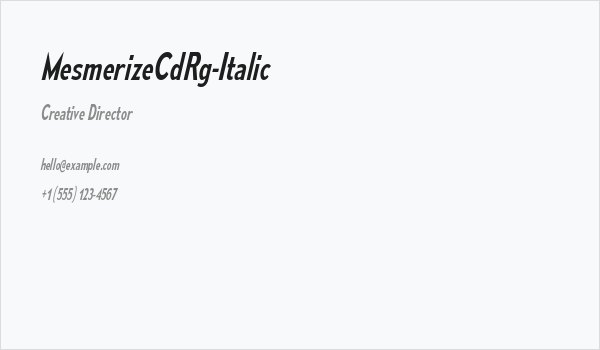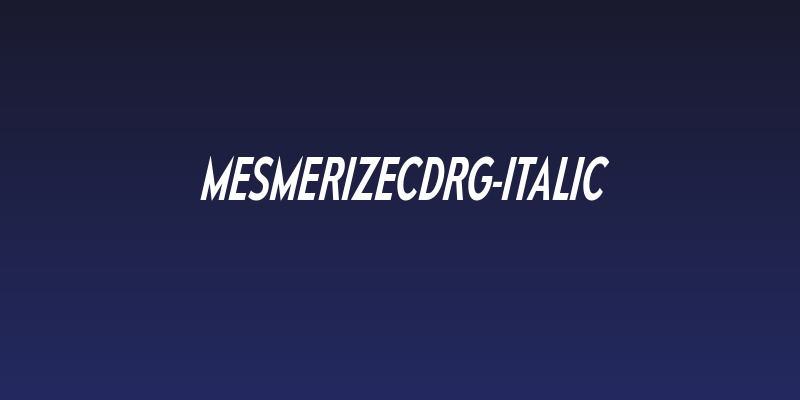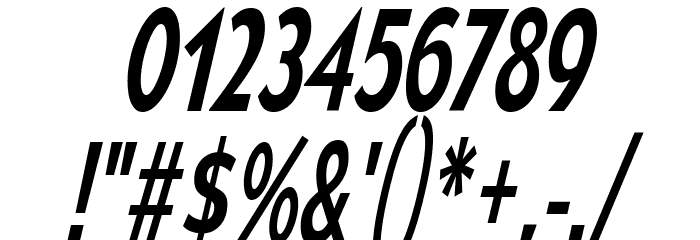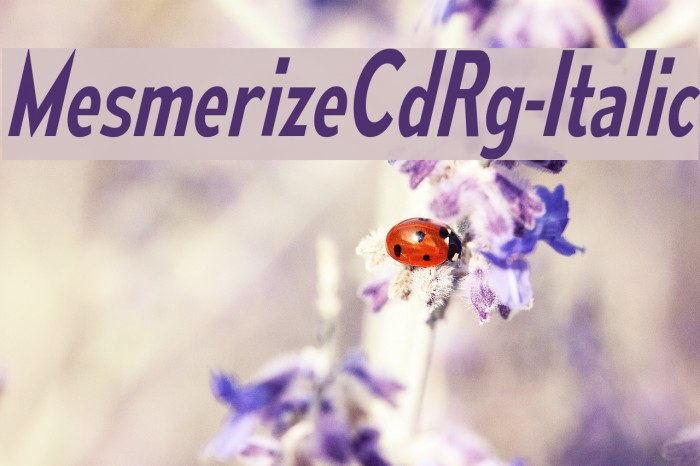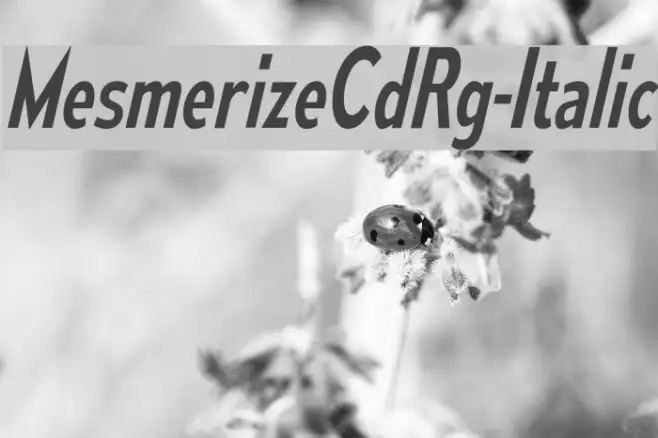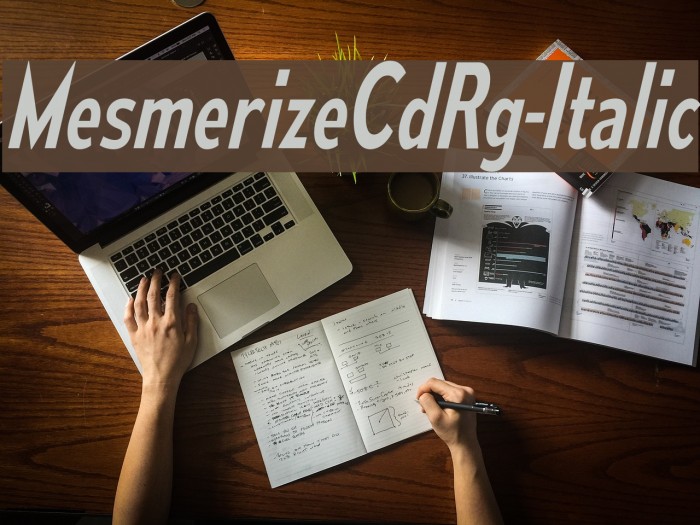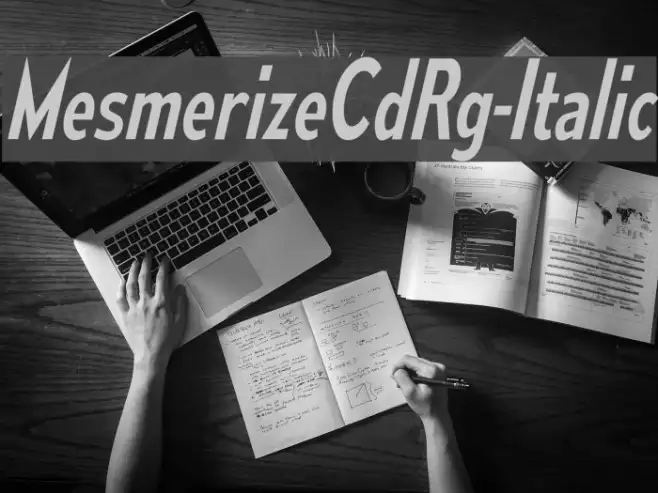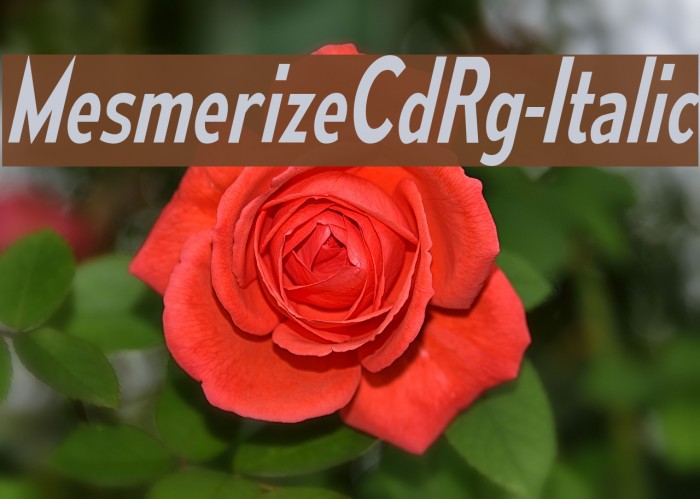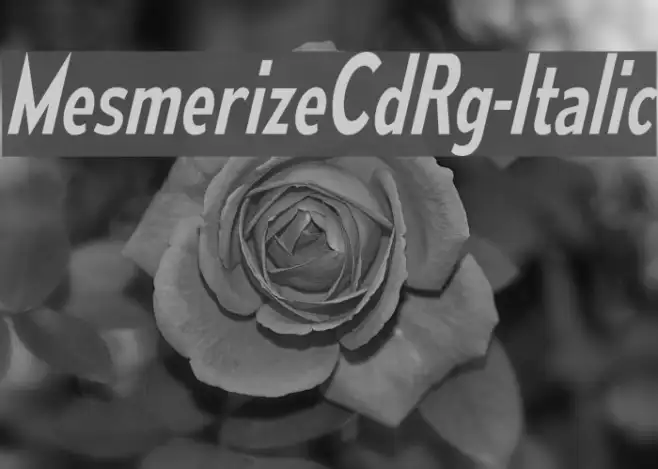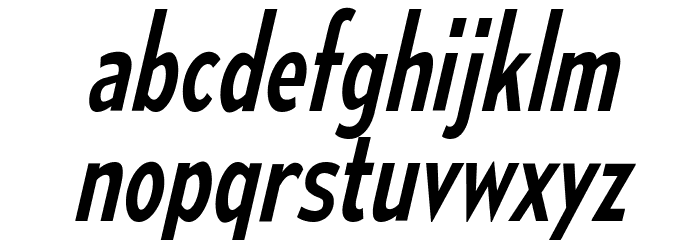
MesmerizeCdRg-Italic Font
| Caso de uso | Headlines, Logos, Advertising |
| Proyectos propuestos | Ideal for branding, advertising, and headlines where a strong and energetic presence is needed. |